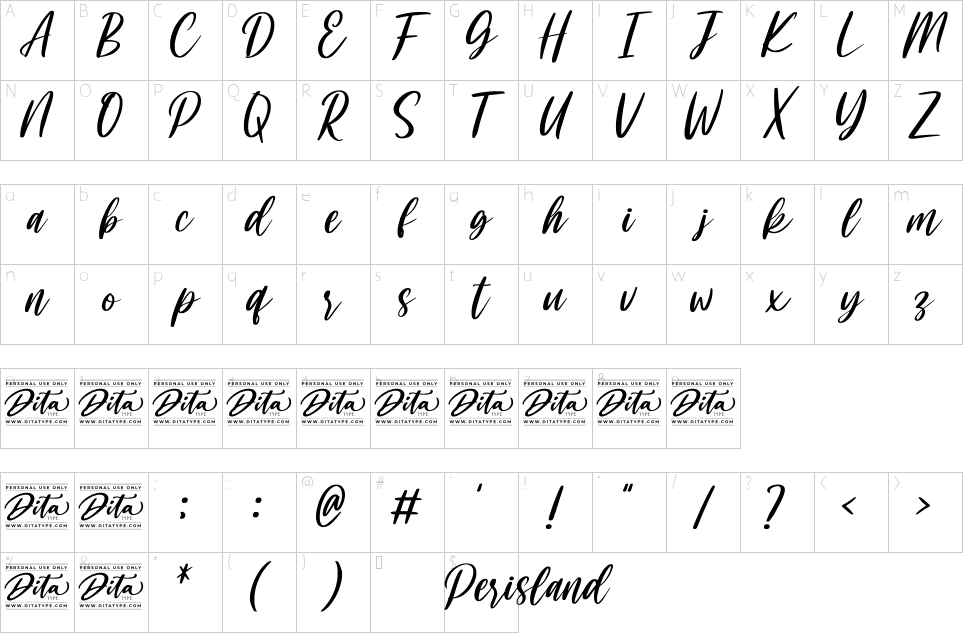
A fonte Perisland é uma grata surpresa para designers e estilistas digitais em busca de uma fonte única e moderna. Criada pela equipe de tipo Dita, Perisland oferece um conjunto de caracteres moderno e versátil, ideal para aplicativos de design gráfico, sites e portais de notícias. Esta fonte é especialmente atraente devido à sua composição única de linhas suaves e interações de cores vibrantes, oferecendo uma experiência visual agradável e imersiva. Com uma estética que se destaca, Perisland é uma escolha ótima para projetos que buscam se destacar e capturar a atenção do público, seja para design de sites, aplicativos ou materiais de marketing digital. Seja você um designer profissional ou um entusiasta do design, Perisland é uma fonte perfeita para sua coleção. Download Perisland agora e deixe seu design se destacar.